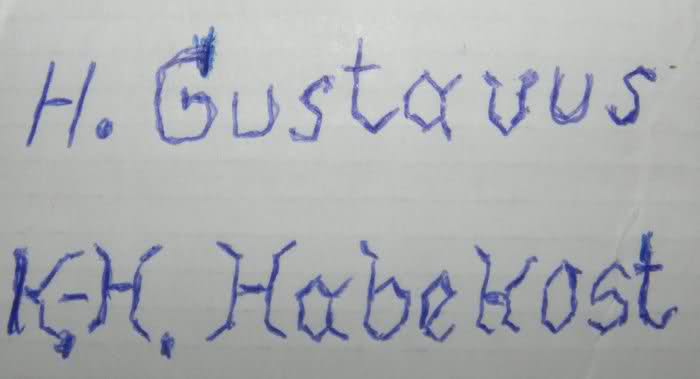
Suche Schrift mit Digitalen und Serifen
Welcher Schriftart könnte die abgebildete Schrift am nächsten kommen?
was meinst Du denn genau mit »Digitalen«? Eine digitale Schrift würde zum Beispiel so aussehen:
Aber das meinst Du nicht, oder? Meinst Du vielleicht Diagonalen?
Das würde für mich jedenfalls mehr Sinn ergeben, wenn ich mir Deine Skizze so anschaue. :-)
Da eine ähnliche Schrift zu finden ist nicht ganz einfach, Deine Vorlage ist recht eigenwillig in den Formen.
Bei einer kurzen Suche bei MyFonts.com habe ich diese hier gefunden:
Und ohne Serifen:
Danke für die Hinweise! Lingua Regular trifft es ja fast. Ich wußte nicht, wie ich die Schrift umschreiben sollte - digitale Zeichen kamen meiner Meinung nach dem am nächsten. Der Urheber der Schriftprobe hat keine Ahnung von Zeichensätzen (besitzt keinen Computer und kennt sich null damit aus). Insofern suche ich auch keine direkt passende Schriftart, sondern nur eine, die der Probe am nächsten kommt.